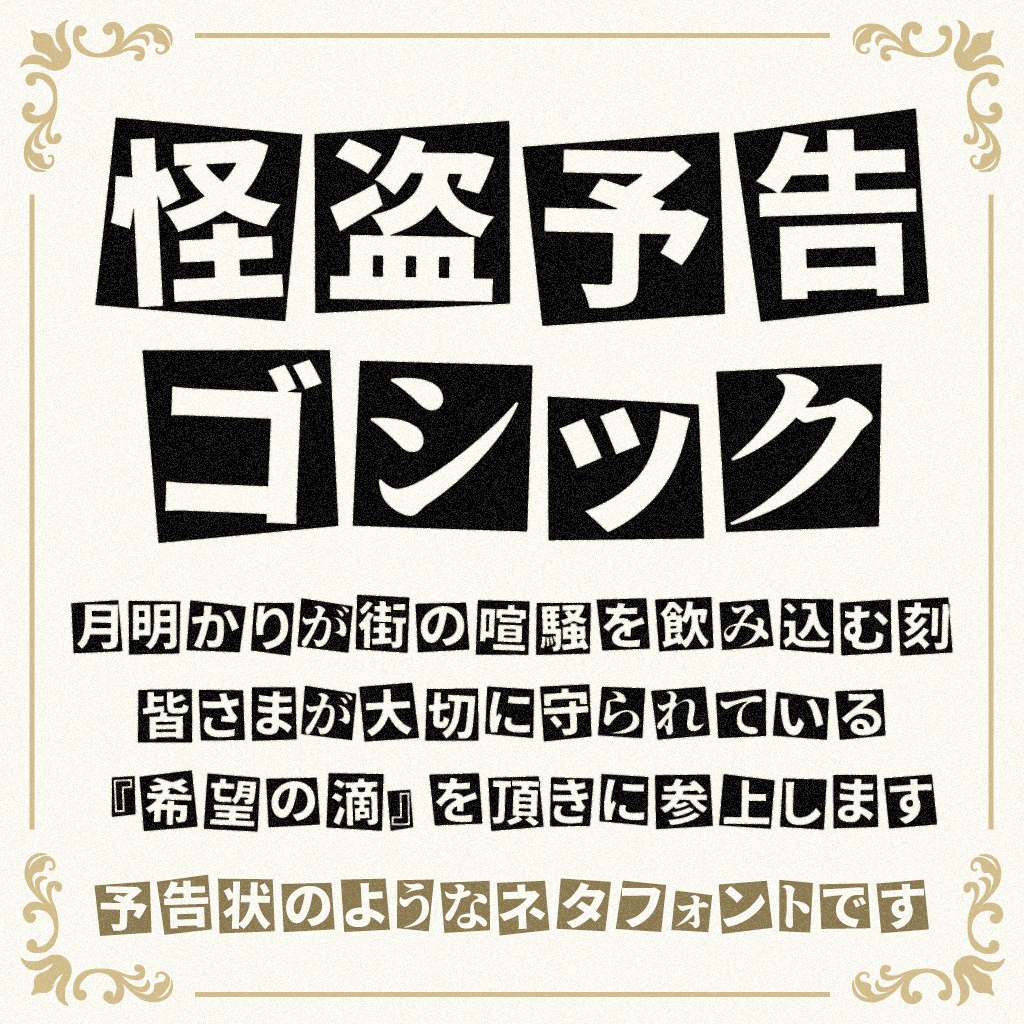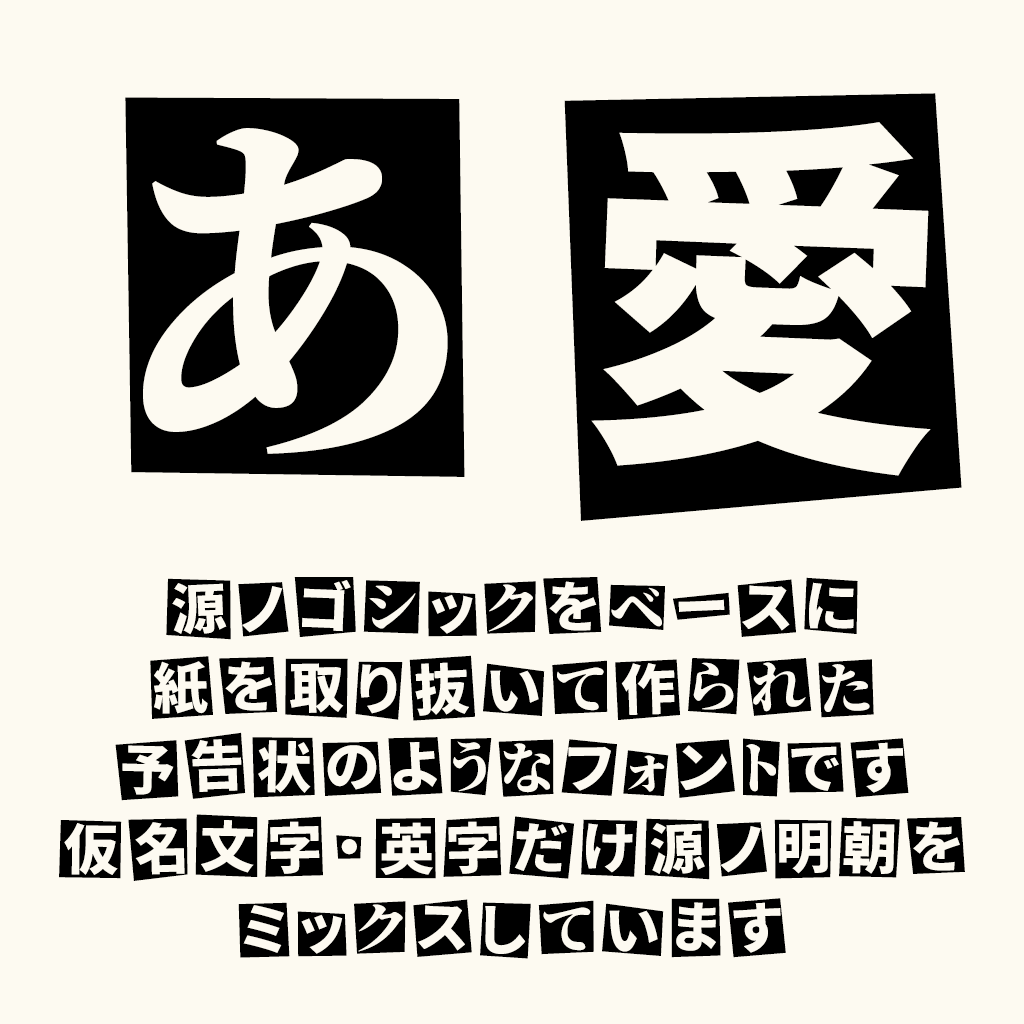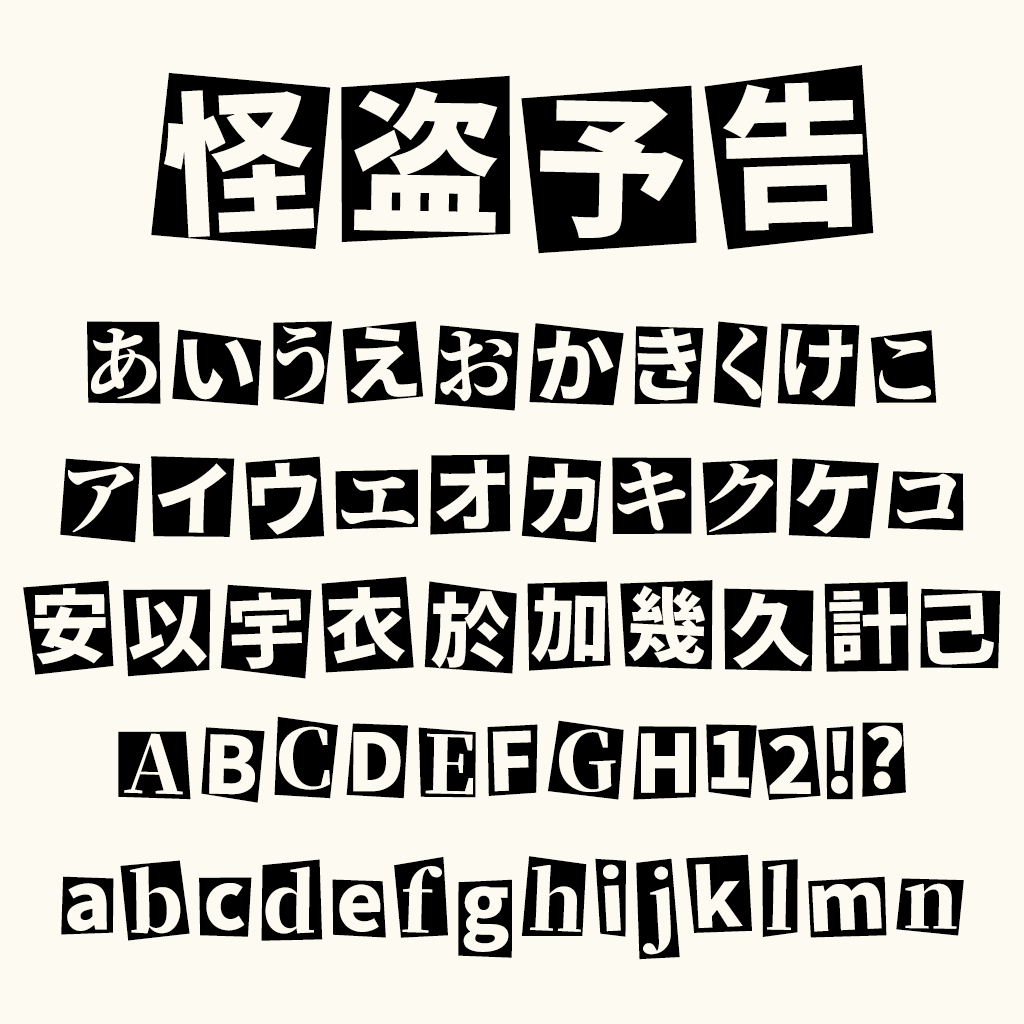
怪盗予告ゴシック
怪盗予告ゴシック是一款以“怪盗预告函”为设计概念制作的日文字体。字体以源ノゴシック为基础进行改造,并在假名与英文字母中融入源ノ明朝(日版思源宋体)的字形特征,通过刻意打乱文字的排列方式,让每个字符呈现出略有差异的角度、大小与位置,仿佛从纸张或报纸上逐一剪下,再重新拼贴组合而成。
这款字体最有辨识度的地方,在于它并没有追求传统字体整齐、规整的排列效果,而是将“剪纸”和“拼贴”的感觉直接融入文字之中。每个字符都像是一块独立裁剪出来的纸片,外围保留着不规则的黑色块面,文字组合后自然形成高低错落、大小不一的视觉节奏。即使只是输入普通的文字,也能够呈现出类似怪盗预告函、匿名信件或旧报纸剪报的特殊效果。
在字形设计上,怪盗予告ゴシック以源ノゴシック作为主要改编基础,使汉字整体依然具有较清晰的结构。而假名与英文字母则加入源ノ明朝的字形元素,并通过不同字符之间的风格混合进一步强化不协调感。这种有意保留下来的“チグハグ感”,并不是字体设计上的缺陷,而是作品希望呈现的视觉特征,让文字看起来更像是临时收集而来的纸片,被随意却又具有设计感地排列在一起。
从实际排版效果来看,怪盗予告ゴシック特别适合用于需要强调氛围感的短文本和标题。黑白对比鲜明的字块能够快速吸引视线,同时不规则的排列方式也让文字本身具有较强的画面表现力。用于悬疑、推理、怪盗、解谜等主题时,可以很好地强化神秘感;用于海报、游戏画面、视频封面、缩略图、活动视觉以及个性化标题设计时,也能够形成比较独特的视觉效果。
除了日文文字之外,字体还包含英文字母、数字以及部分常用符号。英文字符同样延续了不规则纸片与黑色块面的设计方式,因此在进行日文与英文混排时,不容易出现风格完全割裂的问题。尤其是在制作短标题、标语或装饰性文字时,可以利用这种错落的排列效果,让整段文字更接近手工剪贴而成的视觉作品。
怪盗予告ゴシック更适合作为展示字体使用,而不是用于大段正文排版。它真正的特点并不只是某一个字形的笔画变化,而是字符组合后形成的整体视觉效果。因此,在较大的字号下使用,能够更加清楚地表现出纸片切割、随机错位以及黑白拼贴所带来的设计感。搭配旧纸张、报纸纹理、印刷颗粒、黑白摄影等视觉元素,还可以进一步加强这种复古剪报式的氛围。
总体而言,怪盗予告ゴシック是一款非常具有主题性的创意日文字体。它没有单纯从笔画装饰入手,而是将“从纸上剪下文字,再组成一封怪盗预告函”的概念贯穿到字体的整体设计中。源ノゴシック与源ノ明朝的混合、不规则的字符排列以及黑白纸片般的视觉效果,共同构成了这款字体独特的识别度。对于悬疑、推理、怪盗、复古以及拼贴风格的设计作品来说,是一款很有个性化表现力的字体。